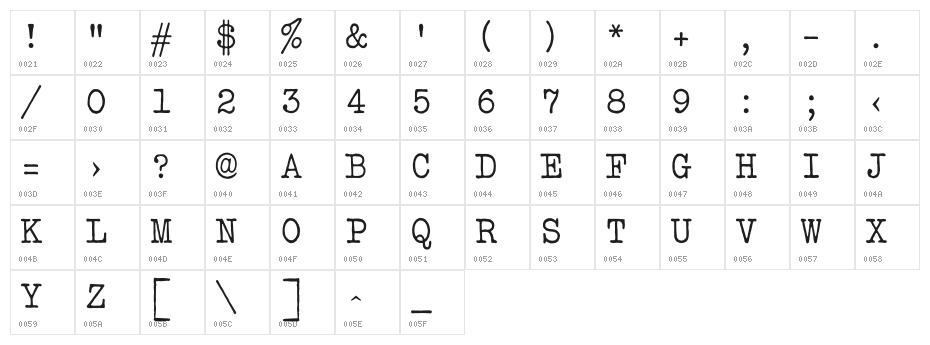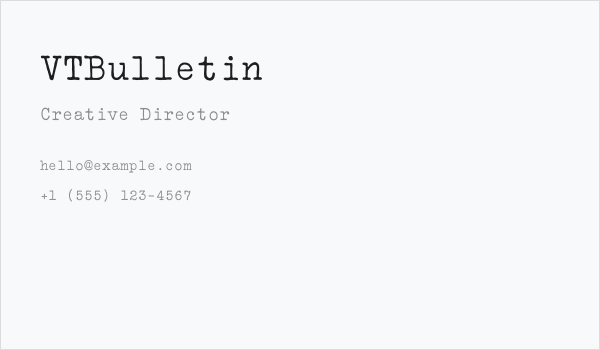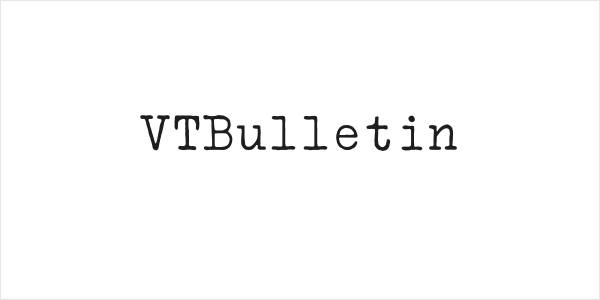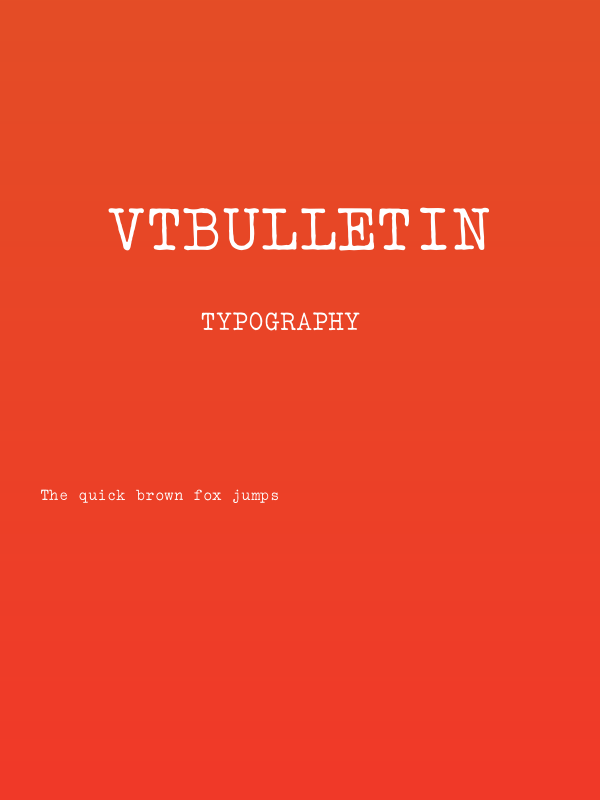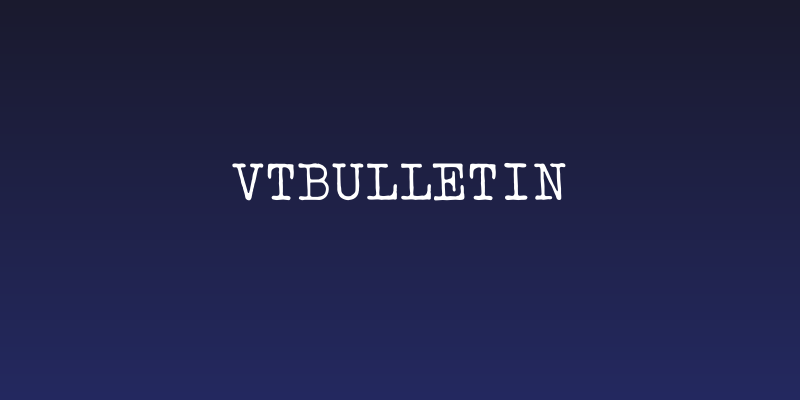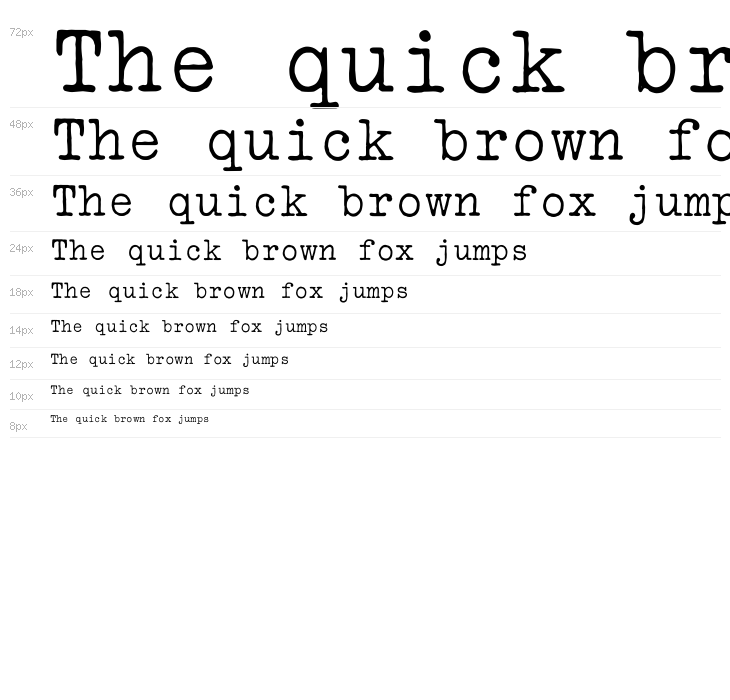
VTBulletin Font
| Gesamtstil | Vintage |
| Anwendungsfall | Headlines, Logos, Coding displays |
| Vorgeschlagene Projekte | Ideal for retro-themed designs, typewriter simulations, coding displays, and vintage posters. |